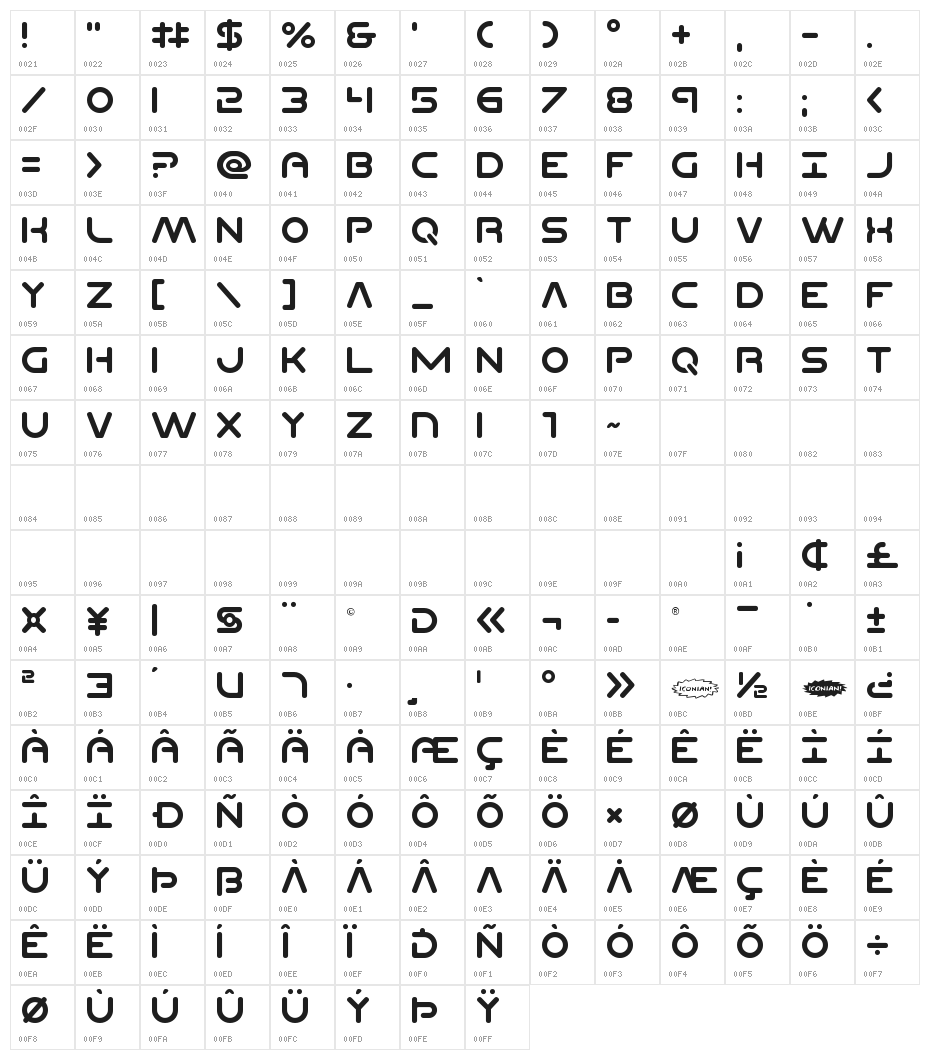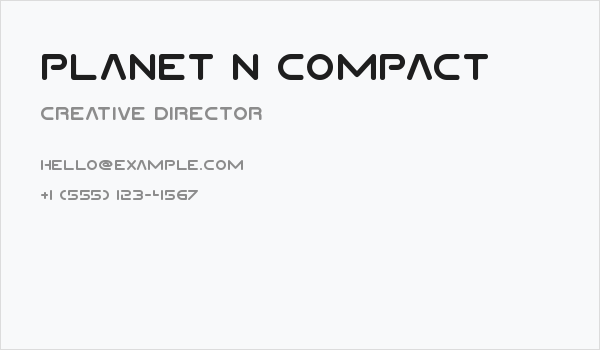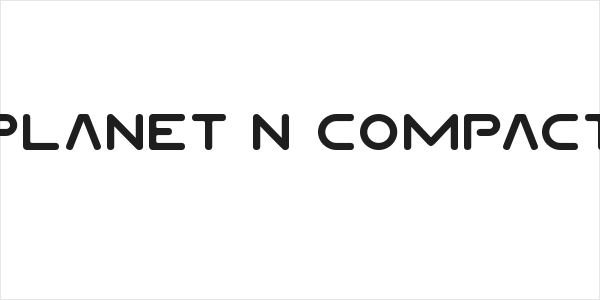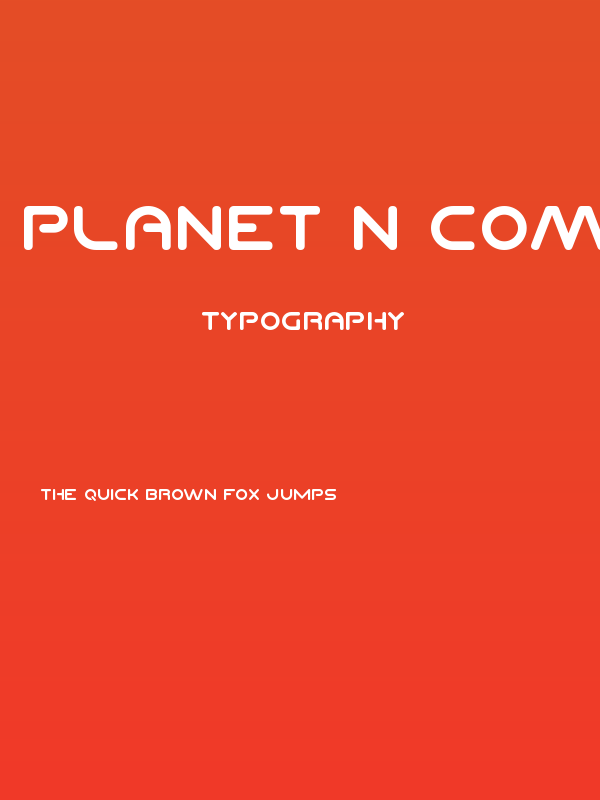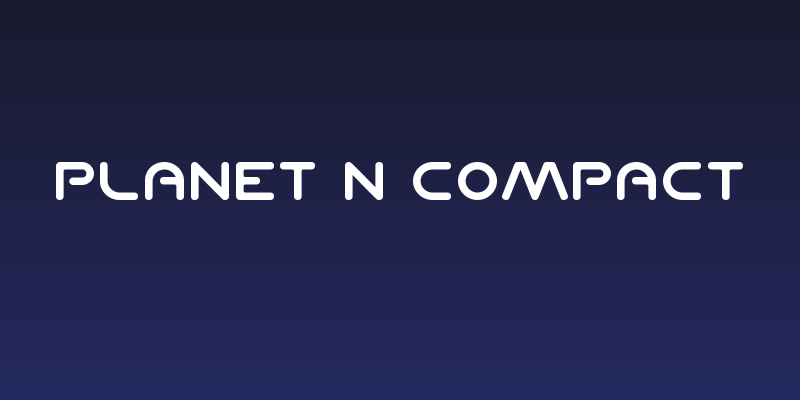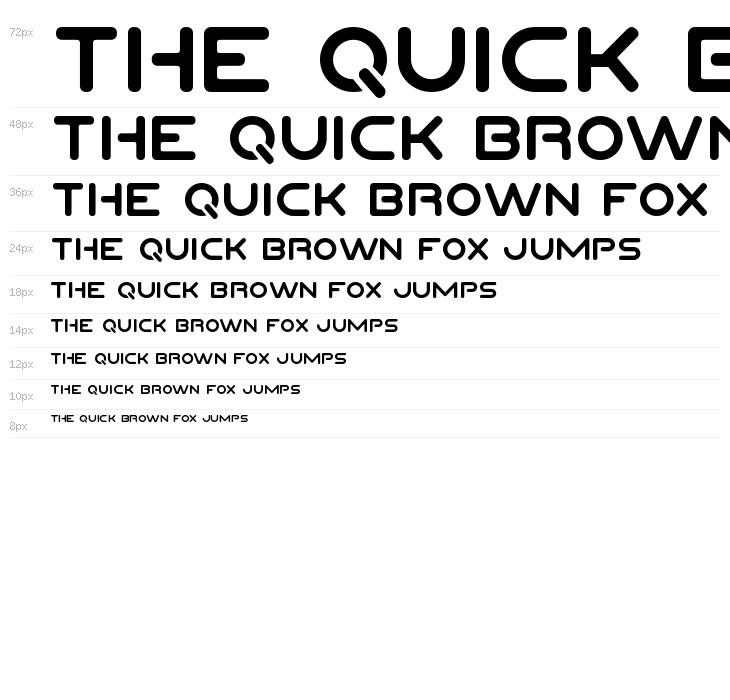
Planet N Compact Font
| Anwendungsfall | Headlines, Logos, Digital Interfaces |
| Vorgeschlagene Projekte | Ideal for technology branding, digital interfaces, sci-fi themed designs, and modern advertising. |